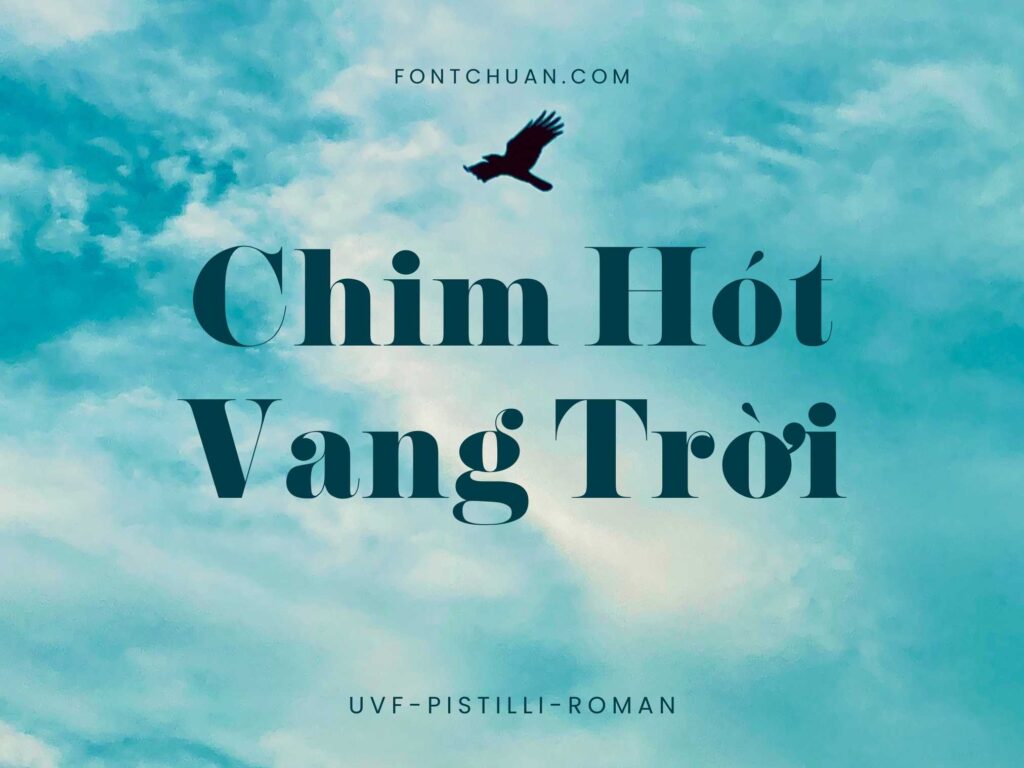
Font UVF Pistilli Việt Hóa
Pistilli Roman là một kiểu chữ serif được thiết kế bởi Claude Pelletier. Font này nổi bật với các đường nét thanh mảnh kết hợp với các nét dày, tạo nên sự tương phản cao và vẻ đẹp cổ điển. Thiết kế của Pistilli Roman lấy cảm hứng từ các kiểu chữ Didone truyền thống, mang lại cảm giác sang trọng và tinh tế cho các dự án thiết kế.
Với thiết kế độc đáo và nghệ thuật, Pistilli Roman phù hợp cho các ứng dụng như thiệp mời, logo thương hiệu cao cấp, bìa sách, hoặc các ấn phẩm đặc biệt, nơi cần tạo ra sự ấn tượng mạnh mẽ về thị giác và cảm xúc. Trong lĩnh vực sự kiện, font này có thể được sử dụng trong các dịp như lễ hội, lễ cưới và các sự kiện văn hóa. Ngoài ra, Pistilli Roman cũng thích hợp cho các ngành nghề như thiết kế đồ họa, nghệ thuật trang trí và xuất bản.